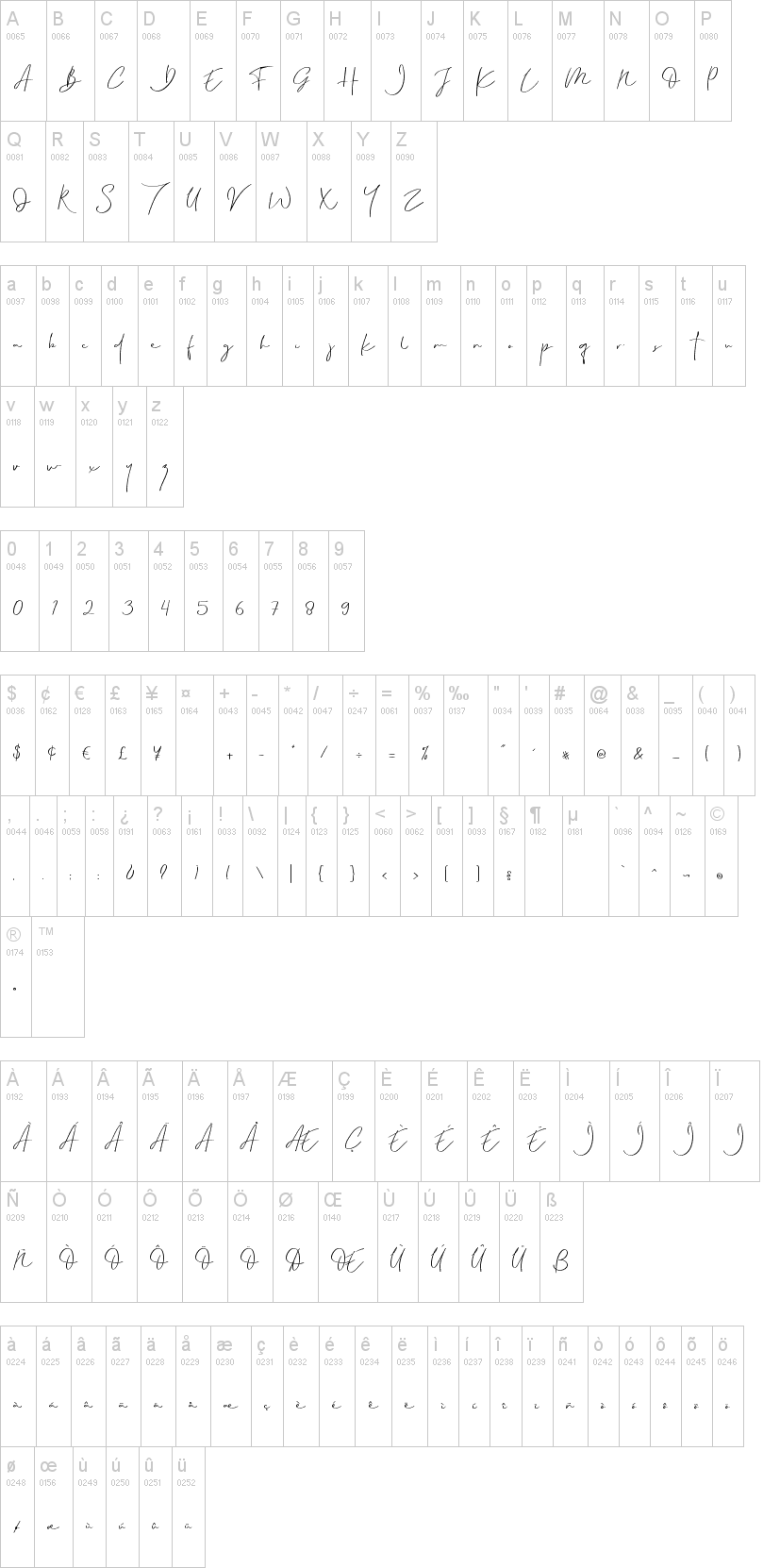
Instalove Diary
? Instalove Diary 字体是一款清新可爱的手写字体,它具有精致的笔画,柔和的曲线,淡雅的色彩,它可以用于拼写单词,制作卡片,设计海报,制作标签等等。它的特点是轻松,可爱,活泼,可以让你的文字更加生动有趣。
Instalove Diary是一款非常不错的手写艺术字体,具有很好的视觉感,适合于文化类的宣传设计、商业类品牌的广告和产品包装设计以及个性化文字排版等较多场景。
Instalove Diary字符映射图